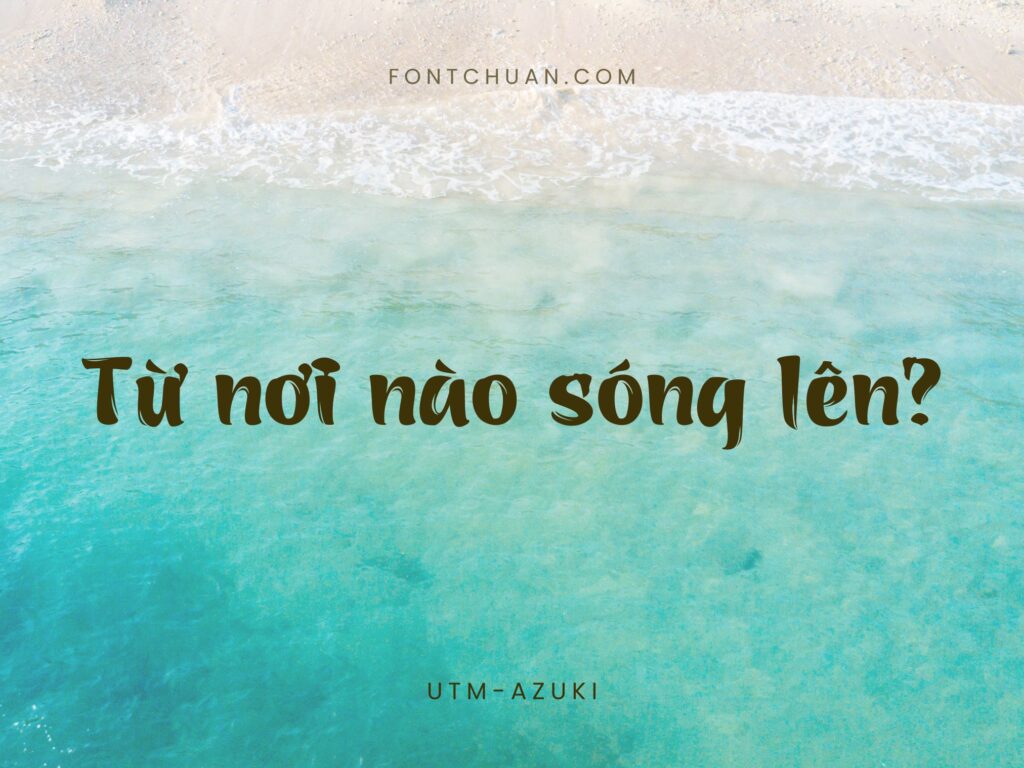
Font UTM Azuki Việt Hóa
UTM Azuki là phiên bản Việt hóa của font chữ Azuki, một Font script được thiết kế bởi Jess Latham. Font này được tạo ra bằng cách sử dụng bút lông Sumi để mô phỏng thư pháp Trung Quốc, với các đường nét mềm mại và tự nhiên, tạo cảm giác thân thiện và gần gũi. Phiên bản Việt hóa đã được thực hiện, hỗ trợ đầy đủ tiếng Việt cùng hơn 100 ngôn ngữ khác. Đây là một trong những font được cộng đồng thiết kế sưu tầm và chọn lọc nhằm đáp ứng nhu cầu đa dạng trong thiết kế.
UTM Azuki có cấu trúc chữ với các nét uốn lượn tinh tế và độ nghiêng nhẹ, mang đậm dấu ấn của Font Handwritten với vẻ đẹp thanh thoát và tự nhiên. Font này phù hợp cho các ứng dụng như thiết kế thiệp mời, tiêu đề, logo và các ấn phẩm in ấn yêu cầu sự tinh tế và cá nhân hóa. Các ngành nghề như quảng cáo, thiệp cưới, giáo dục và ẩm thực có thể tận dụng UTM Azuki để tạo điểm nhấn độc đáo trong thiết kế.